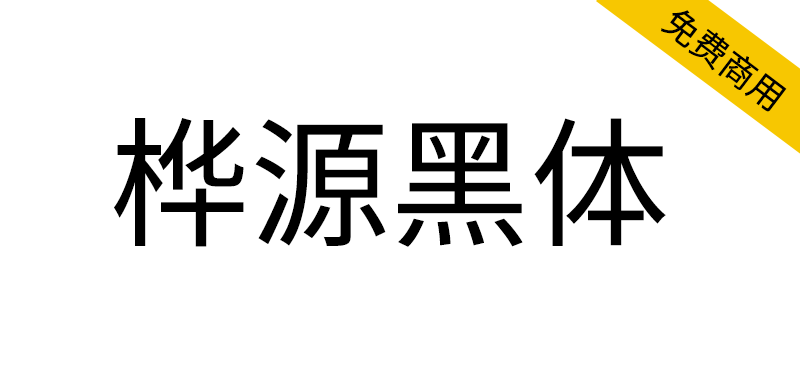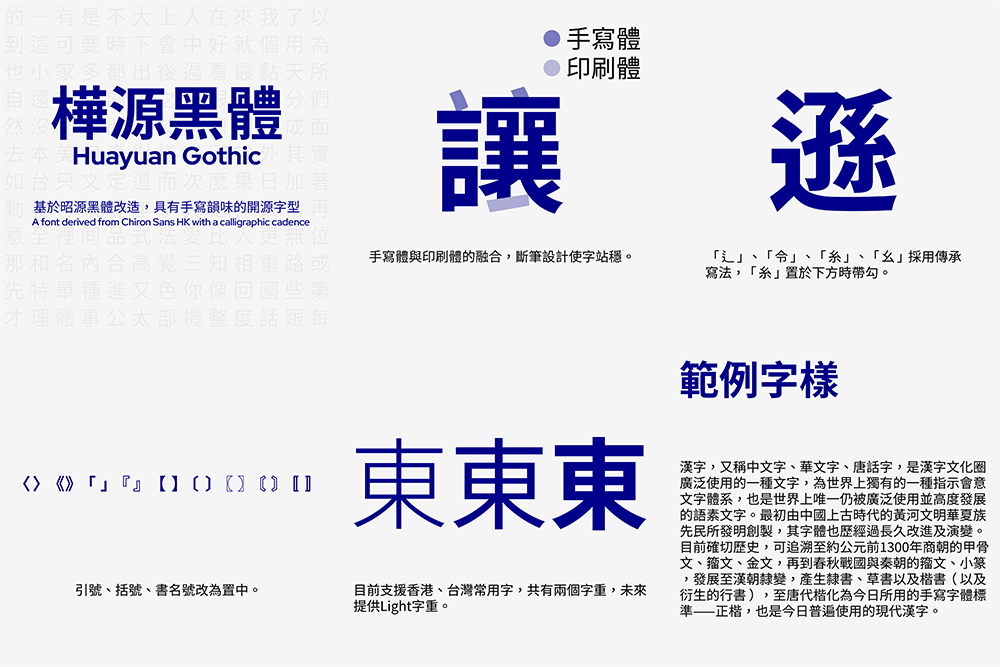
【桦源黑体】基于昭源黑体、思源黑体改造,融合手写韵味
桦源黑体是一套基于昭源黑体、思源黑体改造,融合手写韵味的开源字体。部分字形取自台北黑体。目前支持香港、台湾常用字,共有两个字重,未来提供Light字重。
Huayuan Gothic is a font derived from Chiron Sans HK and Source Han Sans, and integrates handwritten and print features in its design. Some characters are taken from Taipei TC Sans. Currently common characters for Hong Kong and Taiwan are supported, and there are two weights, Regular and Bold. Light will be released in the future.